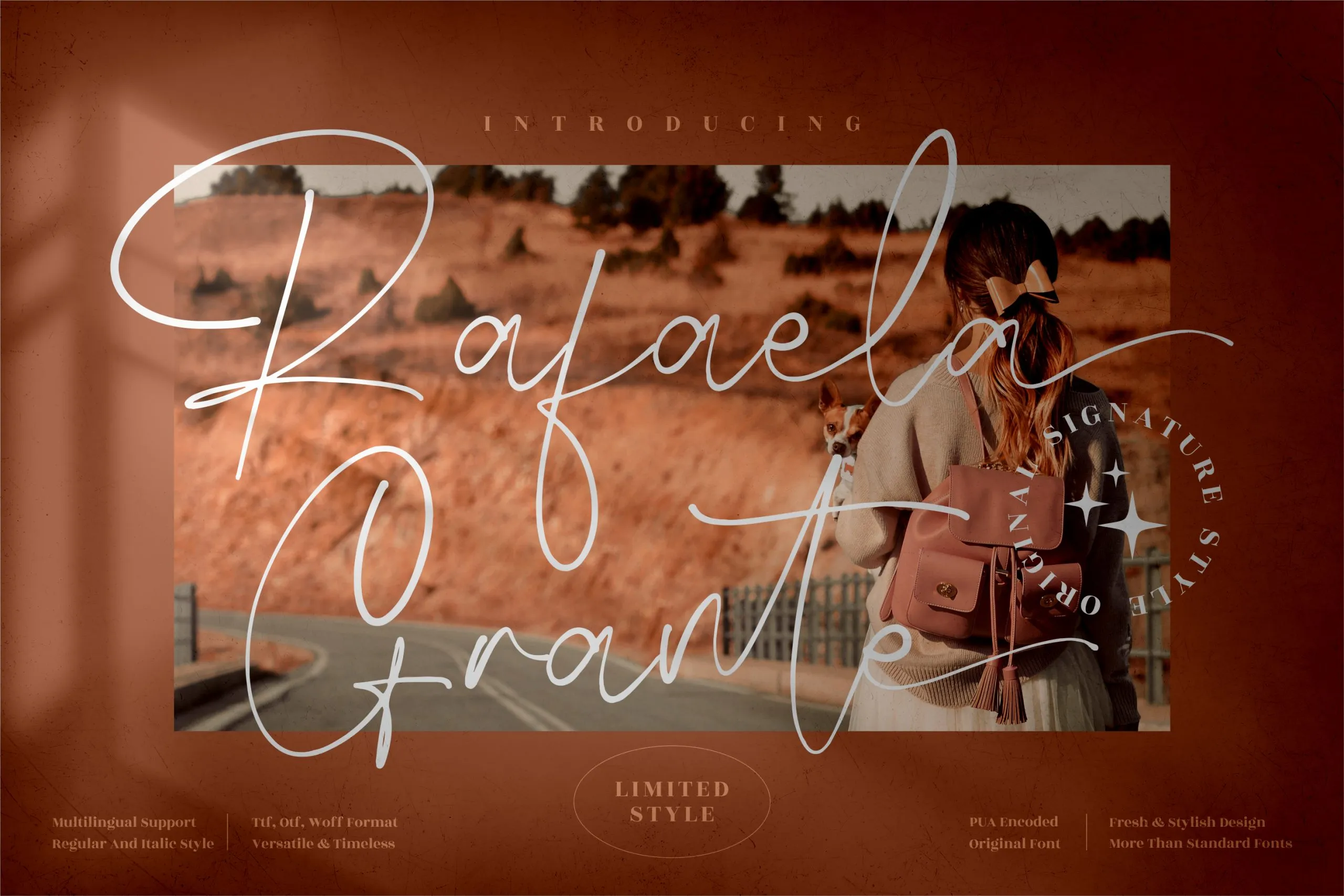
Rafaela Grante Font – Download Grátis
A fonte ‘Rafaela Grante Font’ é uma opção incrivelmente elegante para quem busca uma fonte de签字书法风格的优雅和细腻。来自Perspectype Studio的设计师perspective,为各种项目带来高端签名字体选择,包括LOGO设计、品牌项目、家居装饰、产品包装、马克杯、标语、海报、购物袋、T恤、书本封面、名片、请柬、贺卡、标签、摄影、水印和各种特别场合的项目。不论是追求独特风格还是想为您的作品增添一份高级感,’Rafaela Grante Font’都能成为您项目的理想选择。 无论是用于个人品牌标识,还是企业标志设计,’Rafaela Grante Font’都以其独特的流畅线条、优雅的字体结构和可定制性,为任何项目添加了一抹奢华的气息。这款签名字体不仅适合那些追求专业品质的设计需求,也是创意人士表达个性与风格的理想选择。无论您是平面设计师、图形艺术家还是业余爱好者,’Rafaela Grante Font’都能帮助您的作品脱颖而出,成为独一无二的视觉盛宴。